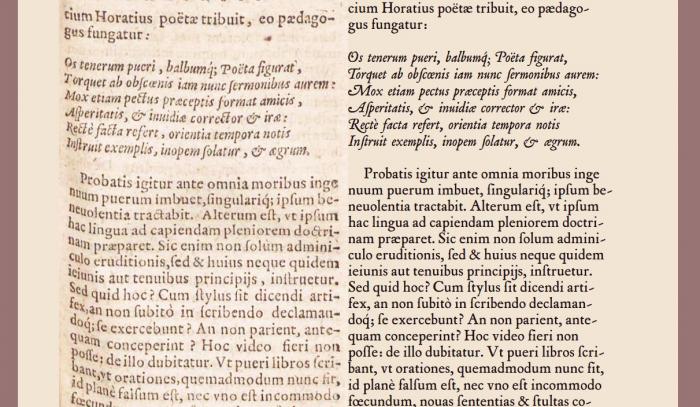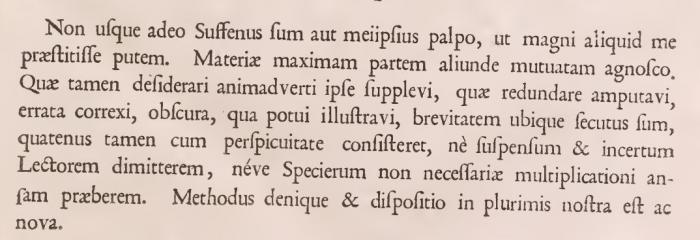
Das Gras war grüner, die Antiqua organischer. Ersatz gesucht!
Betrachtet bitte das Bild im Anhang.
Gefällig fürs Auge ist sie, die Ur-Antiqua, wie wir sie allenthalben aus alten Drucken kennen. Sie wirkt organischer, lebendiger, weicher als viele ihrer modernen Nachfolger. Und ihre Schwester, die Kursive ist selbst in winzigen Schriftgraden gut lesbar. Woran liegt’s und was soll man als Ersatz nehmen? Macht es der geringe Kontrast? die versoffenen Konturen? der halbfette Schnitt? der Tanz der Glyphen außerhalb eines festen Rasters? Ich bitte um Vorschläge für Alternativen! Ich bin sie fast alle durchgegangen die modernern Vertreter, und es ist kaum eine dabei, die ich in kleinen Schriftgraden nicht als beißend, steril, kalt, kantig, fitzlig empfinde.
Du vermischst gerade das optische Erscheinungsbild eines vor vielen Jahrzehnten im Blei gesetzten und auf im Vergleich zu heute rauhem und inhomogenem Papier gedruckten Buchs mit der heutigen randscharfen und qualitativ immer gleichen Druck- und Darstellungsmöglichkeit. Es gibt keine "Nachfolger", solange du völlig verschiedene Techniken betrachtest.
Wenn ich mir den Ausschnitt so anschau, bin ich aber eher über die heutigen Möglichkeiten froh, ich hätte den Text niemals so kompress mit so großen Wortabständen gesetzt. Aber vielleicht bedingt das auch nur die heutige Lesegewohnheit.
@bertel Gescannte Antiqua-Revivals bewirken das gewünschte Schriftbild, nur sind die meisten zu liederlich gescannt.
Was suchst du denn nun? Eine Revival-Antiqua? Einen modernen Vertreter?
ich hätte den Text niemals so kompress mit so großen Wortabständen gesetzt.
Genau, das ist in sich widersinnig (ähnlich wie wenn jemand bei Datumsangaben immer die führende Null dazusetzt, aber das Jahr nur zweistellig schreibt).
@bertel Es kann ein Scan oder Revival sein, muß aber nicht. Z. B. Leipziger Antiqua Demi käme von der Anmutung hin, wären da nicht diese ins Quadratische tendierenden Rundungen. Die Sabon oder dgl. hat mir zu feine Striche.
Die “Felltypes” kommen dem was ich suche sehr nahe. Bisher die beste Alternative. Gibt es weitere Vorschläge? Die Schrift sollte Old Style Figures haben, einen halbfetten oder fetten Schnitt aufweisen, und wenn möglich auch eine Kursive besitzen. Die Kennerly schaue ich mir erst einmal genauer an.
Die meisten dieser Schriften hatten auch diesen langen Schweif des versalen Q: so wie bei der Mazarin hier http://www.flickr.com/photos/bogtrykkeren/7418880648/ Der wurde in den neueren Schriften verstümmelt.
einen halbfetten oder fetten Schnitt aufweisen, und wenn möglich auch eine Kursive besitzen
Das hatten die angestrebten Originale aber nun gar nicht - halbfette oder womöglich fette Schnitte. Weil man sie nicht brauchte. Und eh nur die Schönheit geschmälert hätten ...
Und die Kursiven kamen auch erst ein ganzes Weilchen nach den Ur-Antiquas und brauchten ne ganze Weile, bis sie zur Antiqua eine Harmonie fanden ...
@guteberger Vielleicht sollte ich genauer sagen, daß ich mit “Ur-Antiqua” nicht die allerersten meine, sondern mich gedanklich schon im 16 Jh. befinde. Richtig, sie brauchten keinen halbfetten Schnitt, weil sich die Tinte verlief und die Schrift dann sowieso im Endeffekt fetter erschien als sie war. Ich möchte dieses Druckbild imitieren.
Die Idee, diese Art von Schriften inklusive der Unzulänglichkeiten vergangener Zeiten wieder zu beleben, wurde bereits 1923 mit der Monotype Poliphilus umgesetzt. Wurde damals auch schon mit gemischten Gefühlen begrüsst. Sechs Jahre später gab es den zweiten Versuch, die Bembo. Etwas unbeholfen,  vor allem das geschweifte K, kam jedoch besser an, aber nicht zuletzt weil Monotype ja keine ‘richtige’ Garamond hatte …
Schöne Vorschläge. Besonders die Smooth-Version interessiert mich. Die Mayflower wirkt insgesamt sehr satt, das brauche ich. Die Poliphilus oder Bembo ist leider schon wieder zu “dünn” aufgetragen.
(Bei der Mayflower musste ich allerdings die Bearings noch anpassen, die sind teilweise sorglos gesetzt.)
Hier die Anmutung der Mayflower Smooth; als Surrogat zur Text-Restauration erfüllt sie ihren Zweck erst einmal ausreichend.